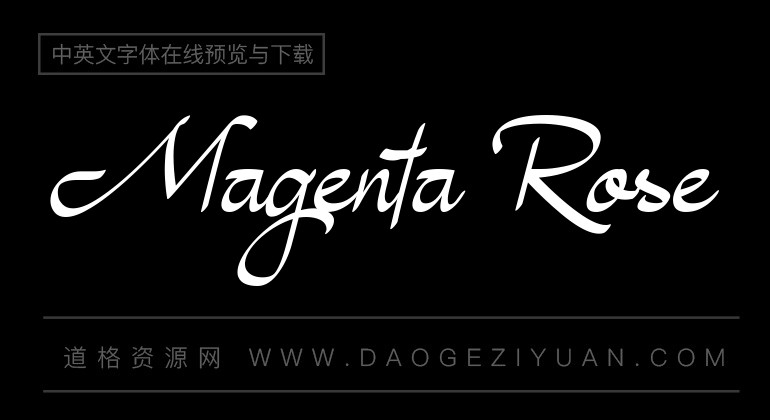
Magenta Rose
Magenta Rose 是一款精美的手写字体,它的特点是细腻而柔和,具有浪漫的气息。它的字体设计主要基于古典的曲线,借鉴了传统的书法风格,具有浓郁的情调。它可以用于创作各种文字,如卡片、小册子、海报、书籍、T恤等,可以添加一种温柔而又浪漫的气息。
Magenta Rose是一款非常不错的手写艺术字体,具有很好的视觉感,适合于文化类的宣传设计、商业类品牌的广告和产品包装设计以及个性化文字排版等较多场景。
Magenta Rose字符映射图